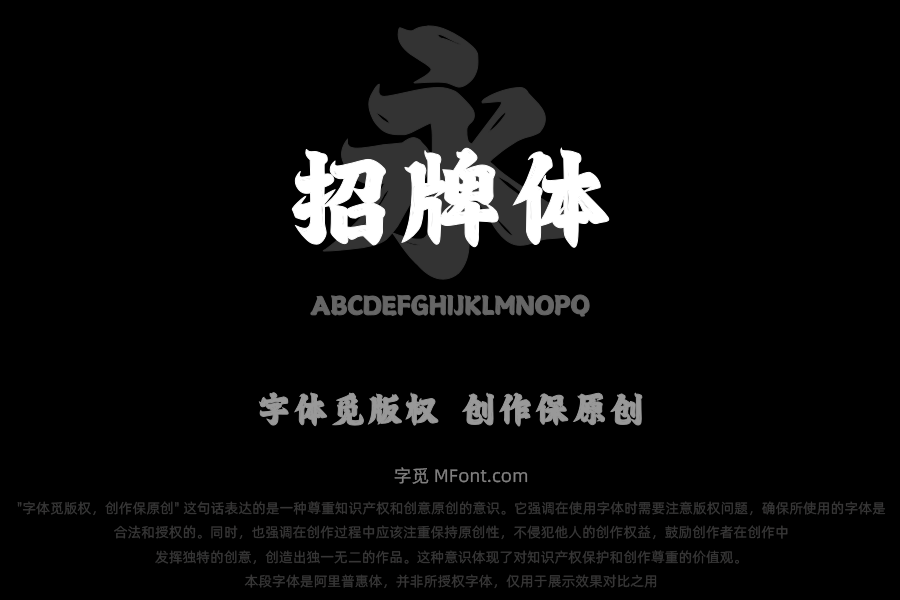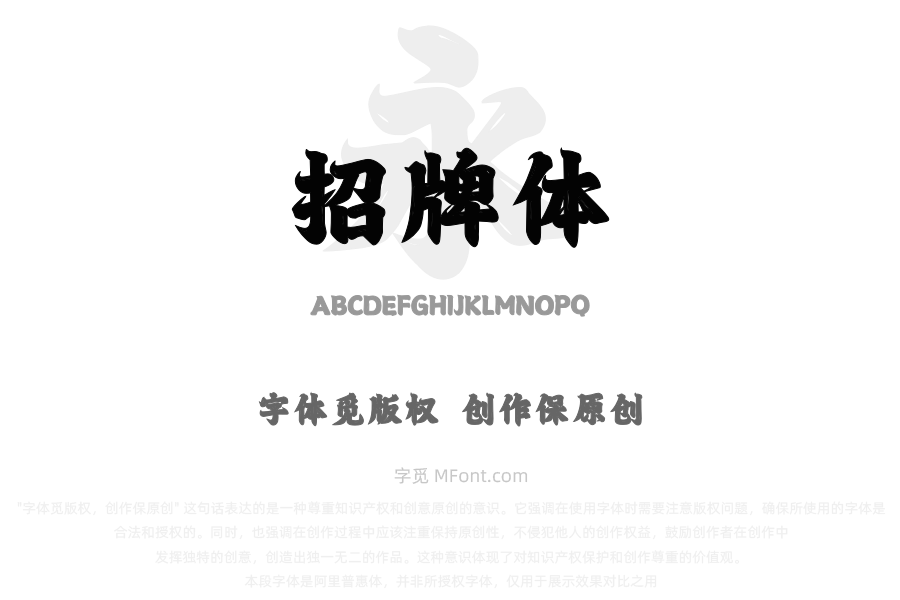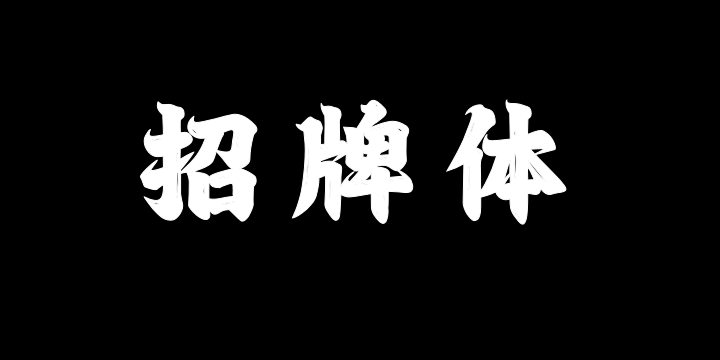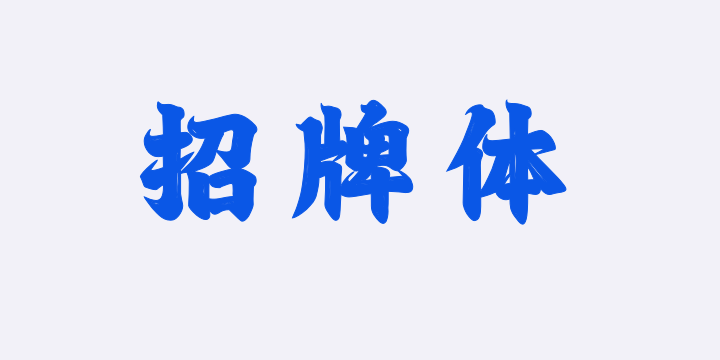
关于上首招牌体字体字库信息
字体全名: 上首招牌体
字体简介: 上首招牌体,简体中文约6763字,字体采用近现代的风格设计,字型整体方正厚重,笔画浑然天成,一撇一捺具有力量感遒劲挺拔,讲究的笔画走势给人强烈的视觉冲击体现出字体大气磅礴,字体端正不失力度,具有大气浑然一体适用于搭配标志、广告标语、商业广告等高端属性。